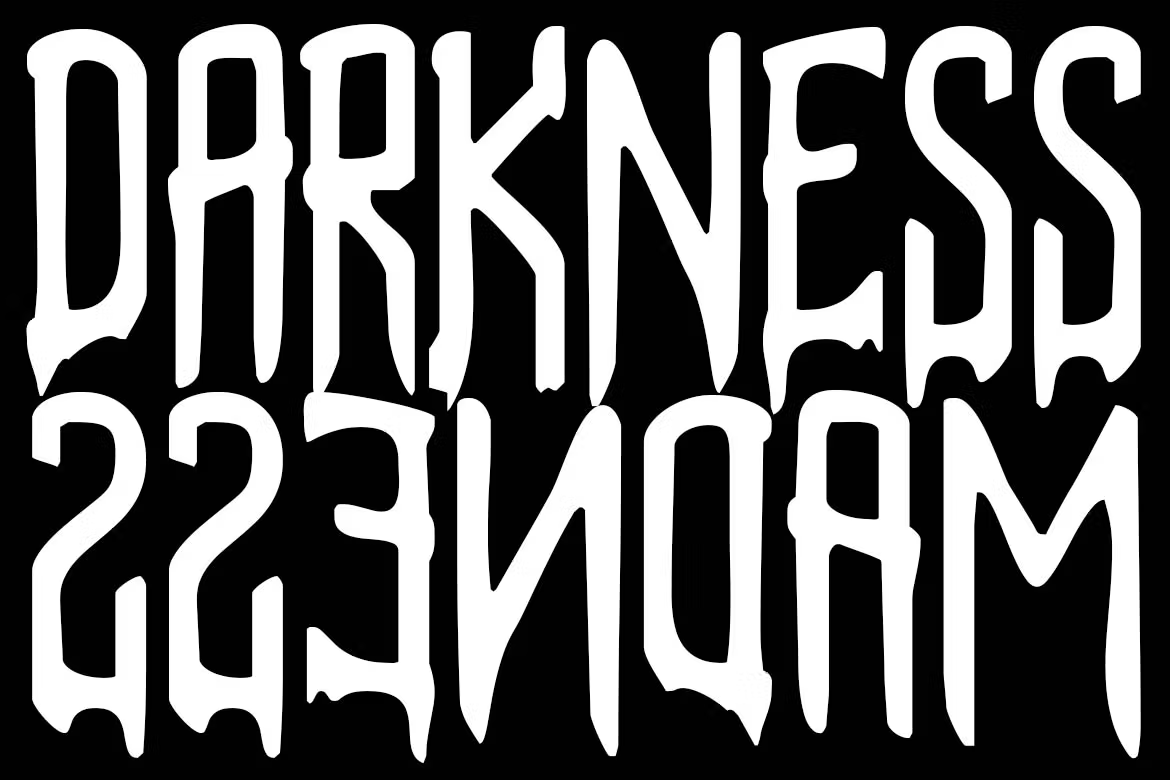
DROWNING Font
Drowning Font n’est qu’une police d’horreur. Si vous aimez le design sombre, utilisez simplement cette police pour votre projet. cette police a un look d’horreur supplémentaire lorsque vous la voyez. merci